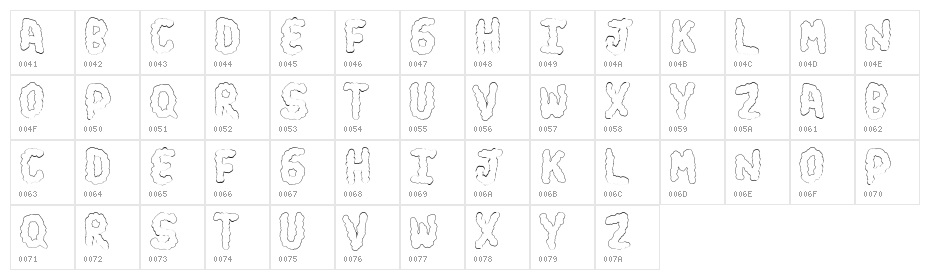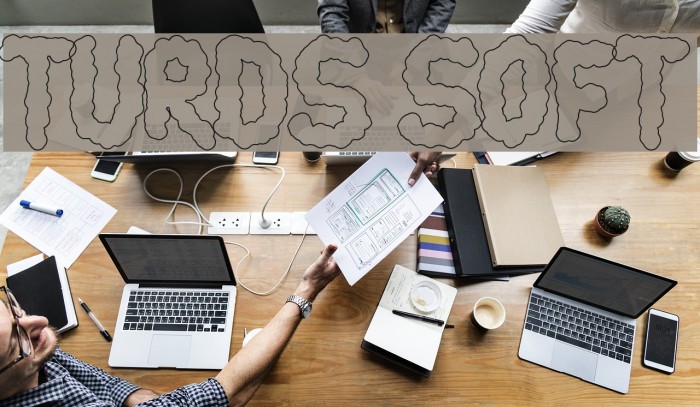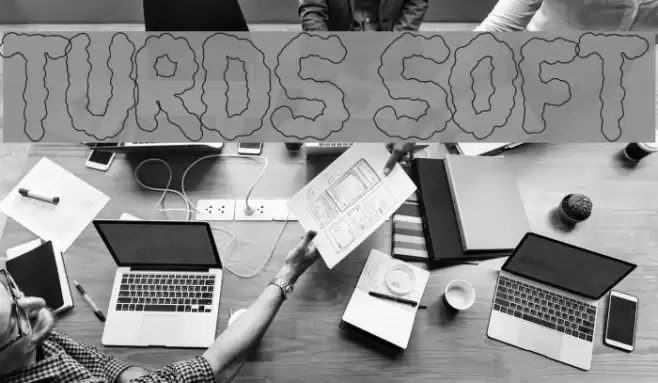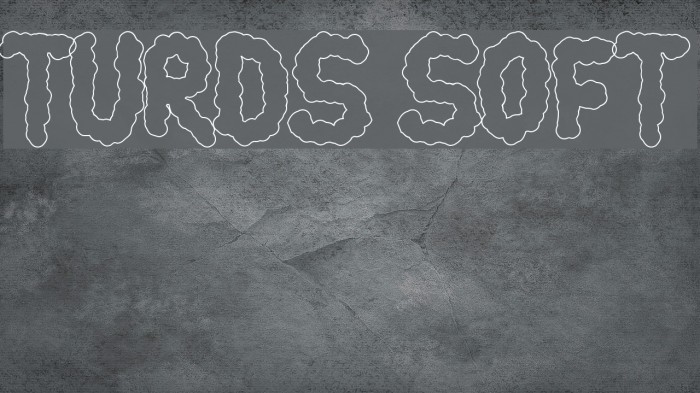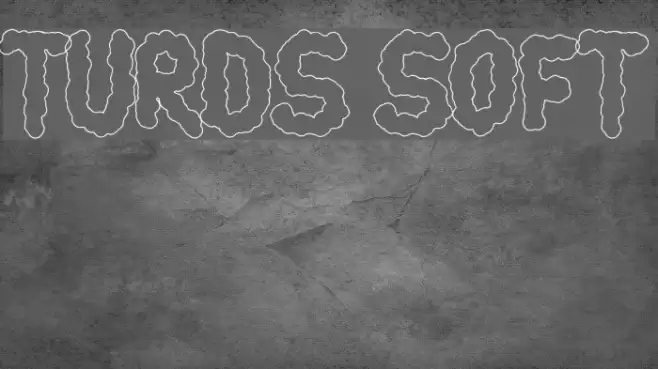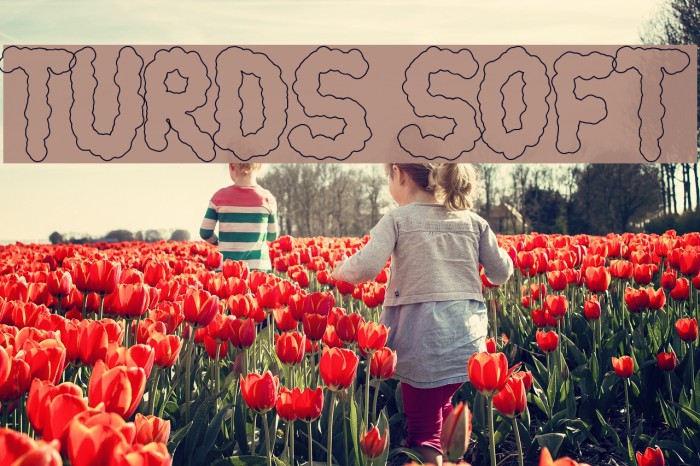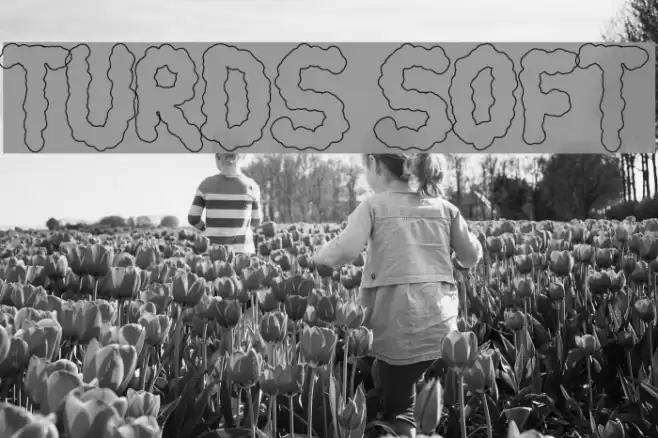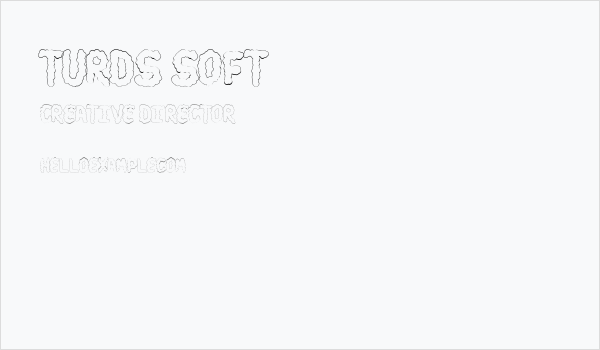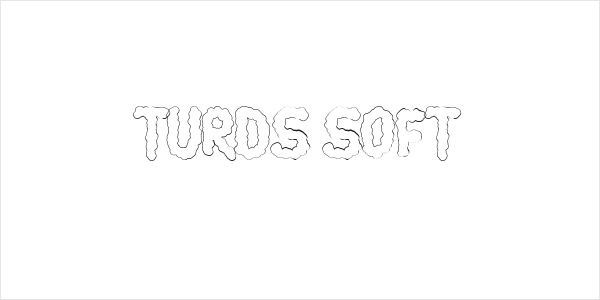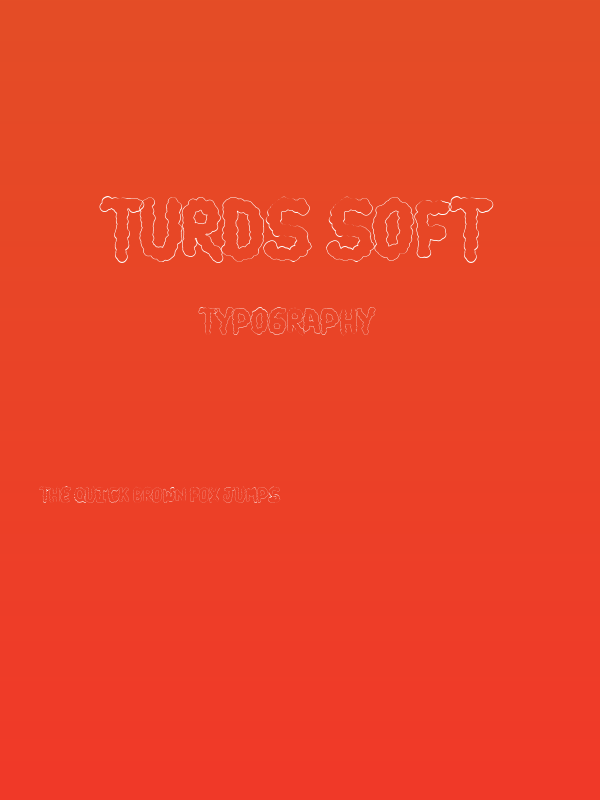
turds soft Font
| Gesamtstil | Whimsical, Playful |
| Vorgeschlagene Projekte | Ideal for children's books, playful branding, party invitations, and creative posters. |